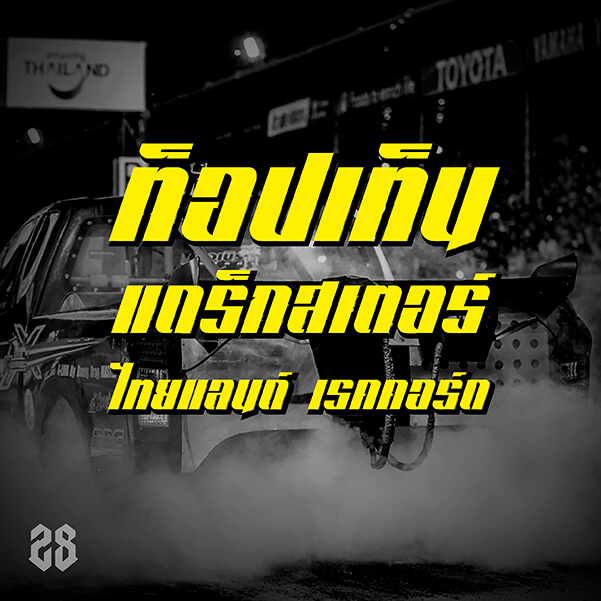
วันแมนโชว์™ (OneManShow™)
วันแมนโชว์™ (OneManShow™) ซึ่งเป็นฟอนต์ลำดับที่สองของผม โดยได้แรงบันดาลใจมาจากกีฬาความเร็วและการแข่งขัน Motorsport ต่างๆ โดยฟอนต์วันแมนโชว์™ (OneManShow™) เป็นแบบตัวพิมพ์ที่ออกแบบ จัดทำ และแจกฟรี โดยสามารถนำไปใช้ในงานออกแบบได้เลยครับ (ใครใช้ฟอนต์วันแมนโชว์แล้วนำมาอวดกันด้วยนะครับ ^^)